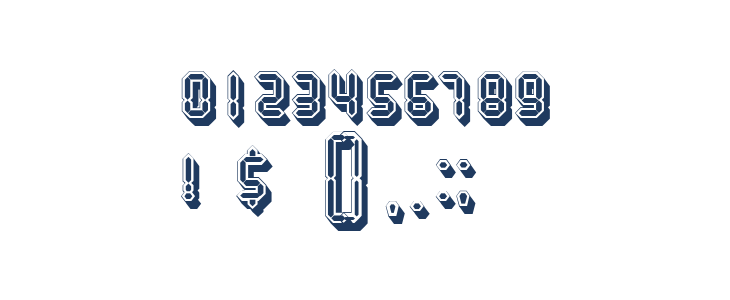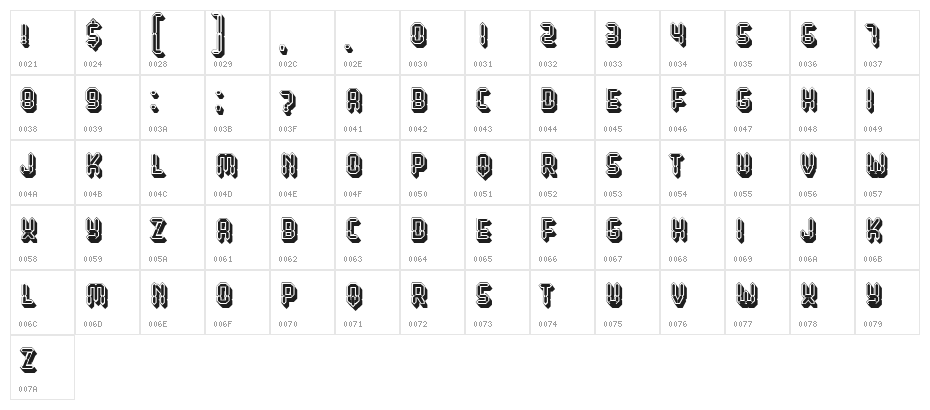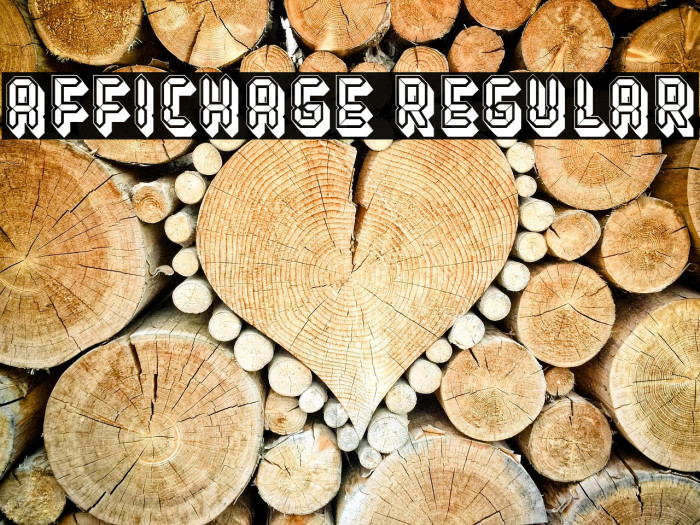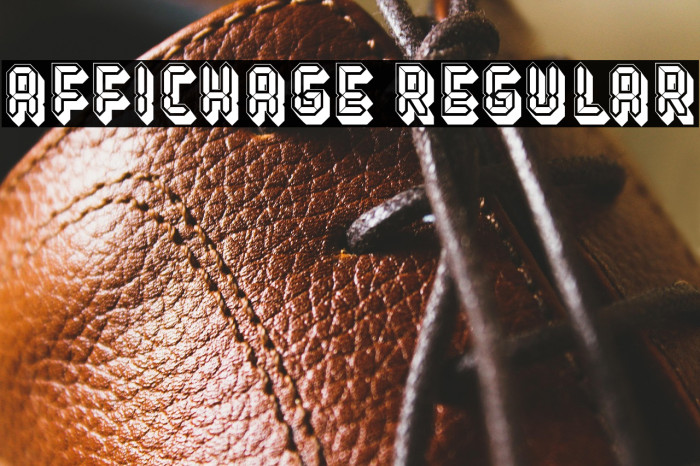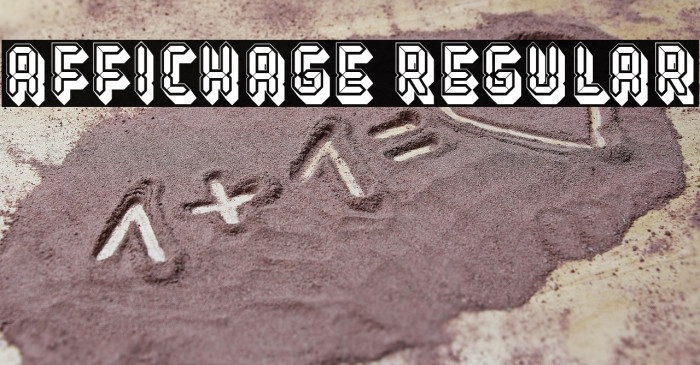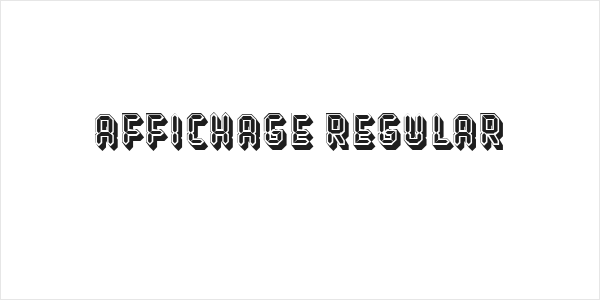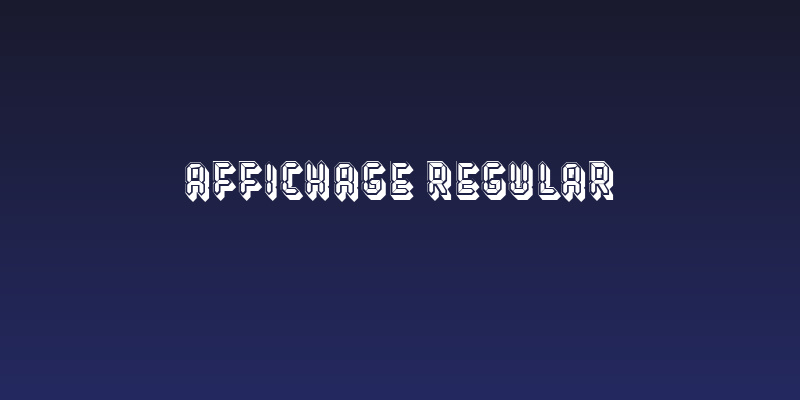
Affichage Regular Font
| Gesamtstil | Retro, Modern |
| Vorgeschlagene Projekte | Ideal for poster designs, retro-themed branding, video game graphics, and eye-catching headlines. |
Affichage Regular